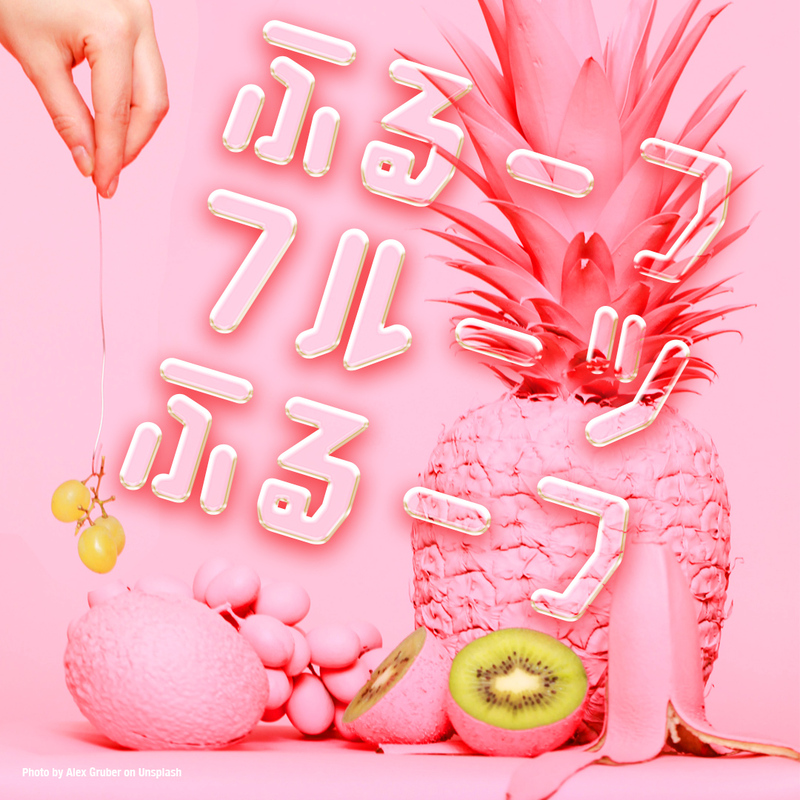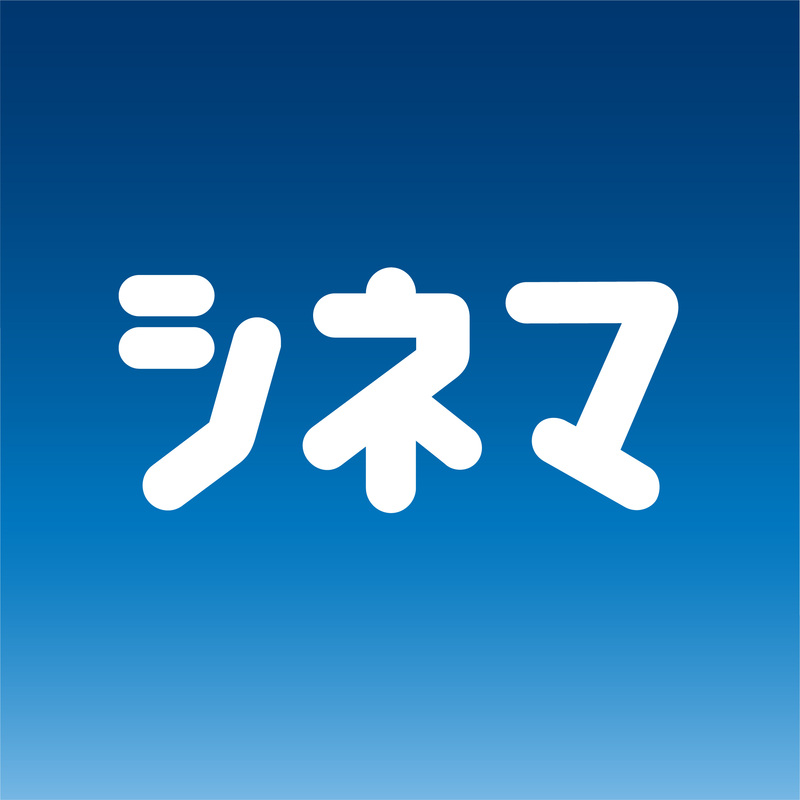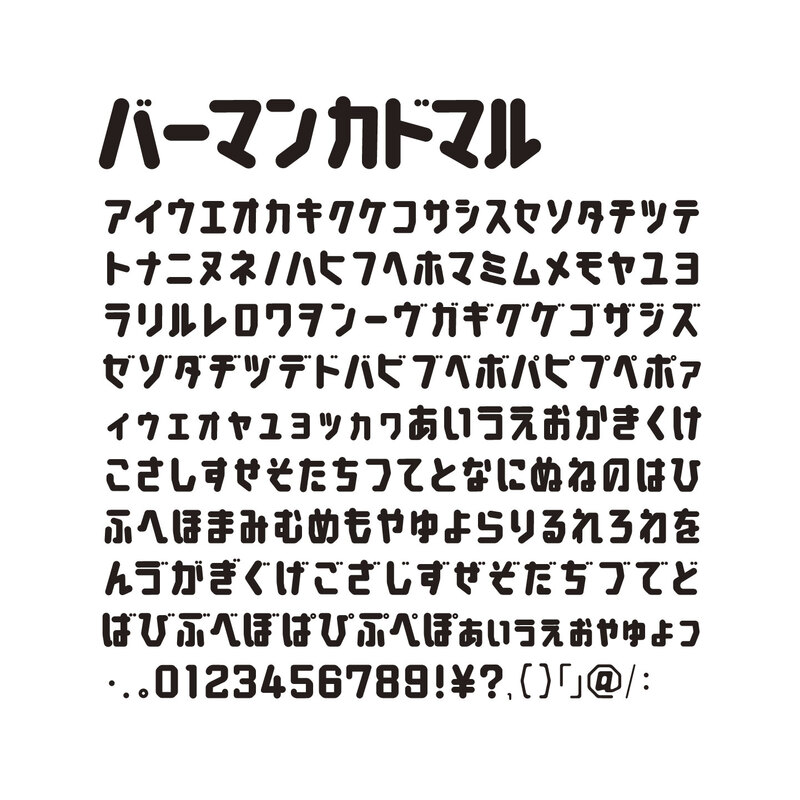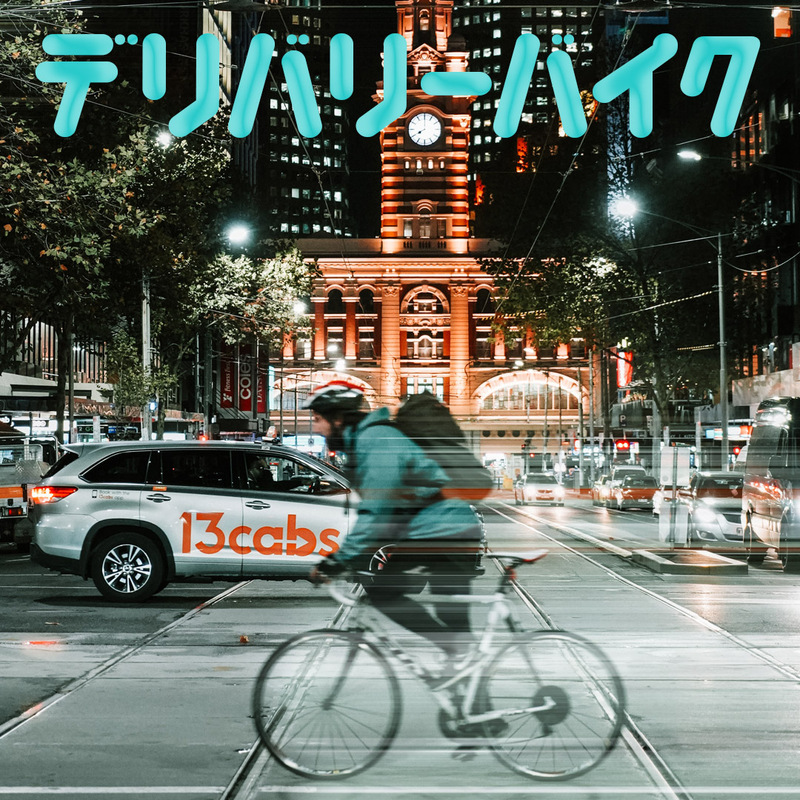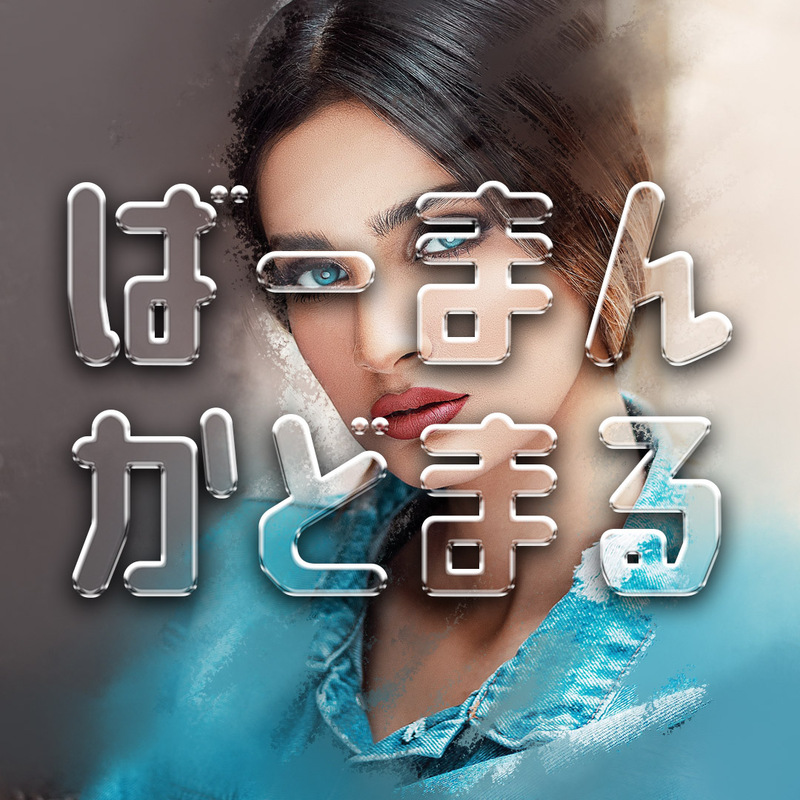
バーマン カドマル|Chiba Design|和文・欧文・デザイン書体のダウンロード販売|フォントファクトリー
直線と角のふところを大きめにしたスタイル。ショップのロゴ、POPの作成などに便利です。角を丸めてキュートな感じに仕上げました。ひらがな・カタカナのみ・アウトライン抽出可。商用利用okです。